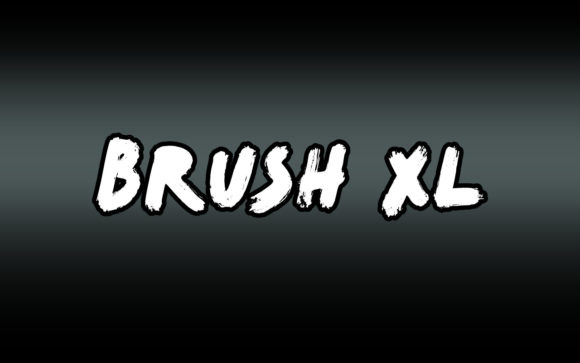
Creating Your Own Handwritten Style Font
Trouver les bons éléments de conception peut être un défi, mais Creating Your Own Handwritten Style Font propose une collection exceptionnelle qui rehausse instantanément votre travail.